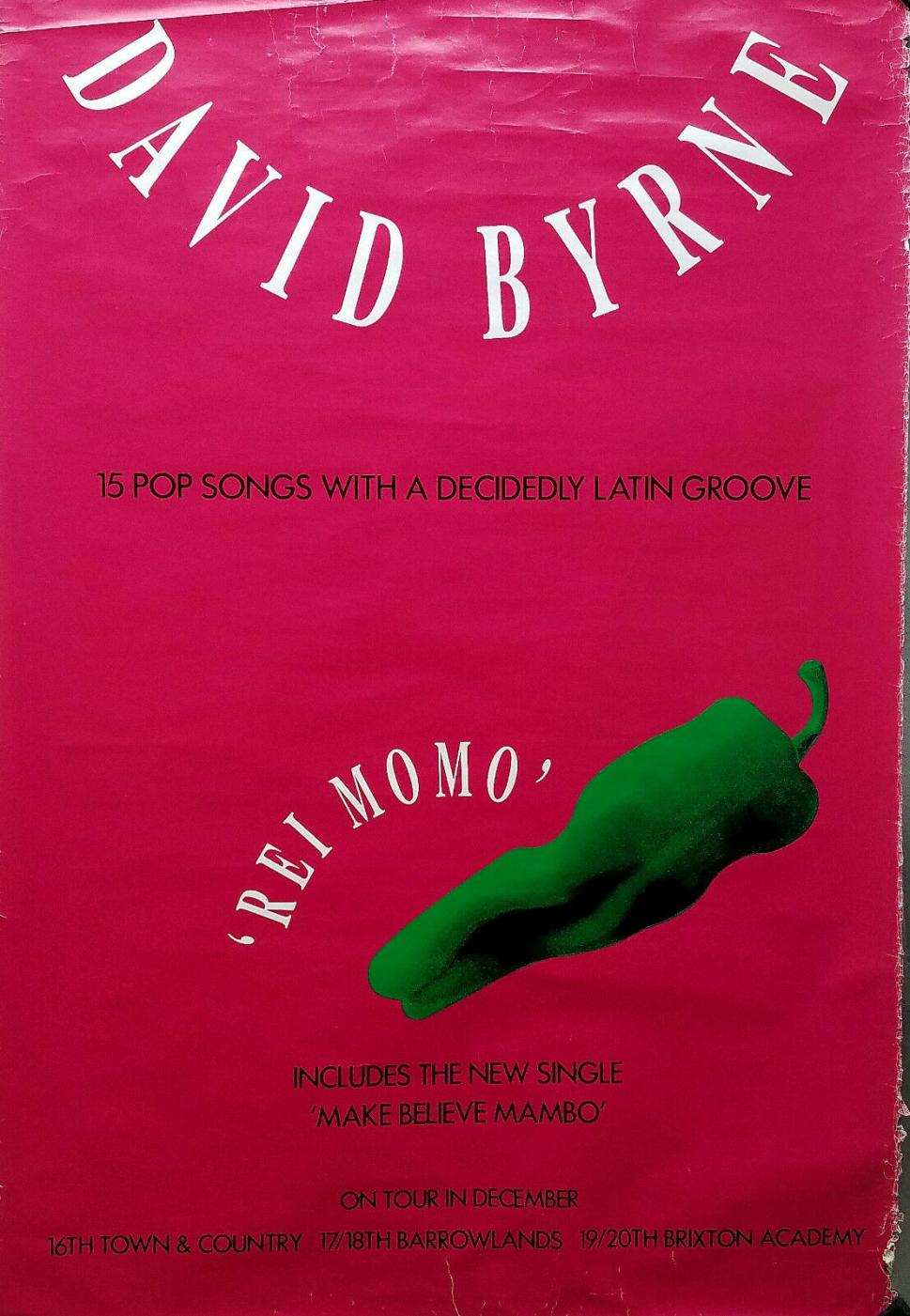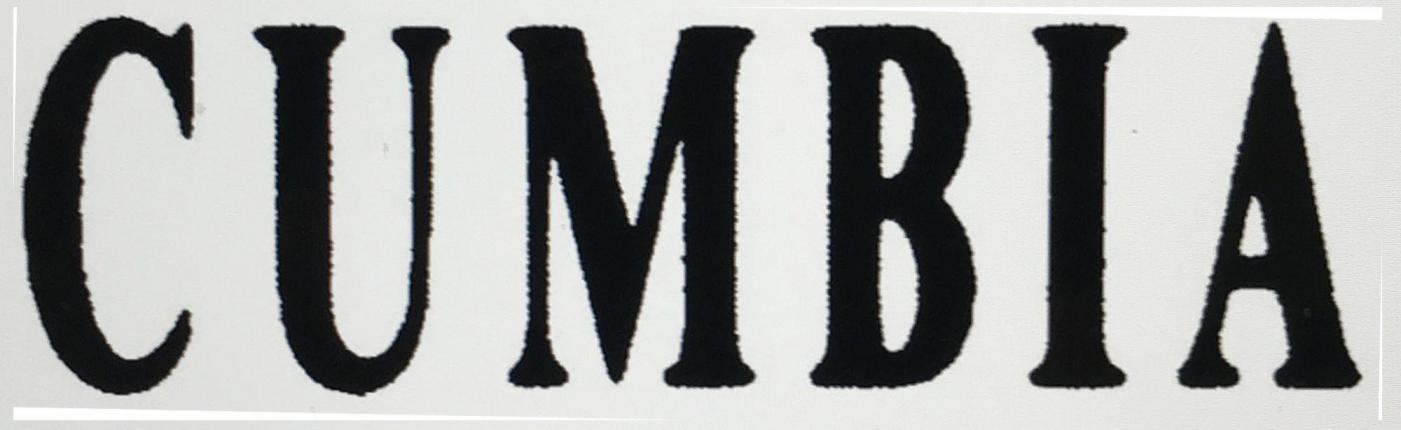
Schriftart im Wort "CUMBIA" (Rei Momo)
habe mich im Internet wund gesucht nach der Schriftart im angehängten Bild, habe aber leider außer den nachfolgenden Fonts nichts wirklich Passendes gefunden:
- Soul Of Vodka (Freefont)
- TheReconLegendFont (Freefont)
- Cheltenham Bold ExtraCondensed
- Gloucester Bold Extra Condensed
Ich könnte die genannten Fonts zwar in Notfall für meinen Zweck (Neusatz) verwenden, aber da alle sich in Details vom Bild unterscheiden, habe ich die Hoffnung, dass jemand von euch die originale Schriftart erkennt und benennen kann.
Die Schriftränder sind übrigens glatt (das ist ein Screenshot eines entrasterten Copydot-Files).
Schriftgrößen bewegen sich zwischen 6 und 12 Punkt - und alles in Versalien.
Es darf gerne auch ein kommerzieller Schriftschnitt sein.
Kein Problem, es geht um den Neusatz einer CD Inlaycard (David Byrne's "Rei Momo").
Es liegen nur noch Copydot-Files (hochaufgelöste Scandaten der Filme vor).
Die Abbildung ist nicht wirklich gut, aber die Einzige, die ich im Internet finden kann.
David Byrne "Rei Momo" Inlaycard
Es geht im Wesentlichen um das Tracklisting und – falls der passende Font benannt werden kann – um alle anderen Texte, die dann mit selben Schriftschnitt gesetzt werden.
Ich wäre auch eher bei einer Times, wenn ich mir das Bild unten so anschau … dein Beispiel hat runde/abgerundete Serifen, das entspringt eher einem anderen Font.